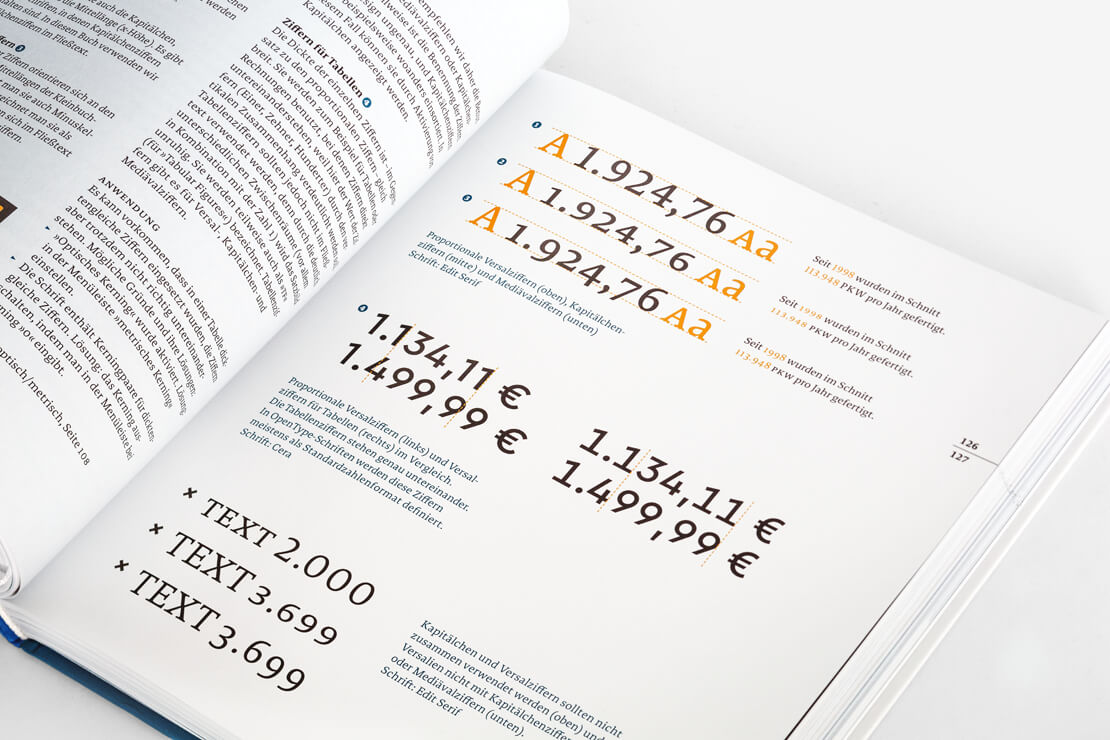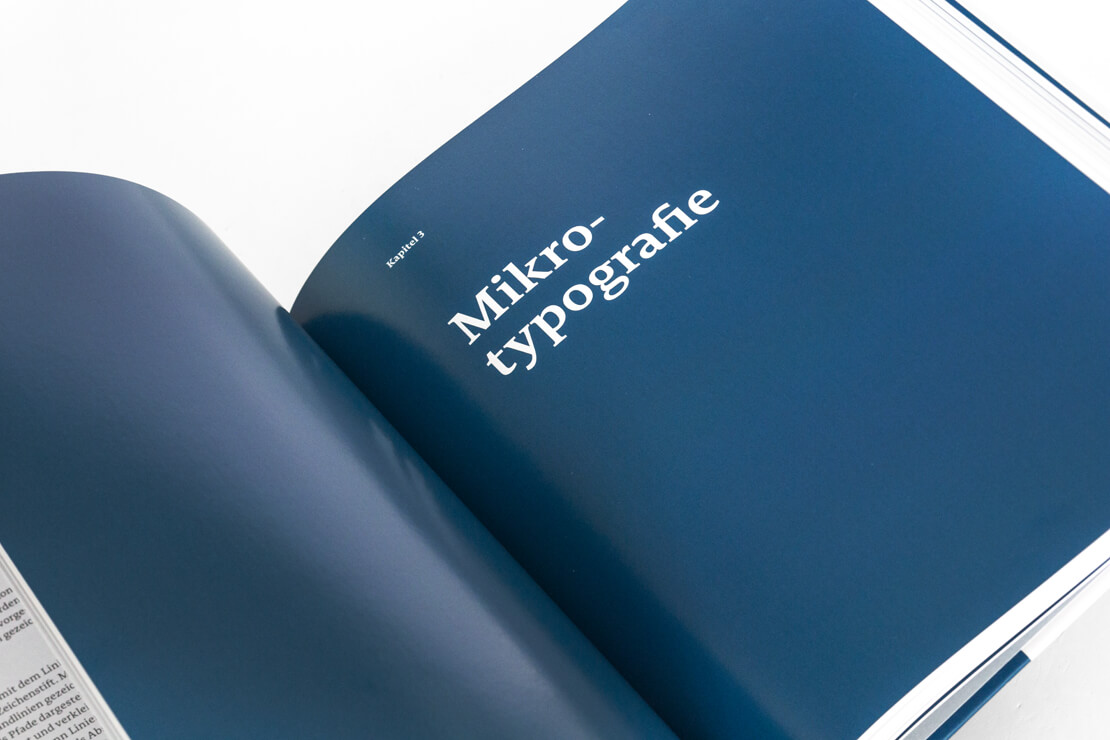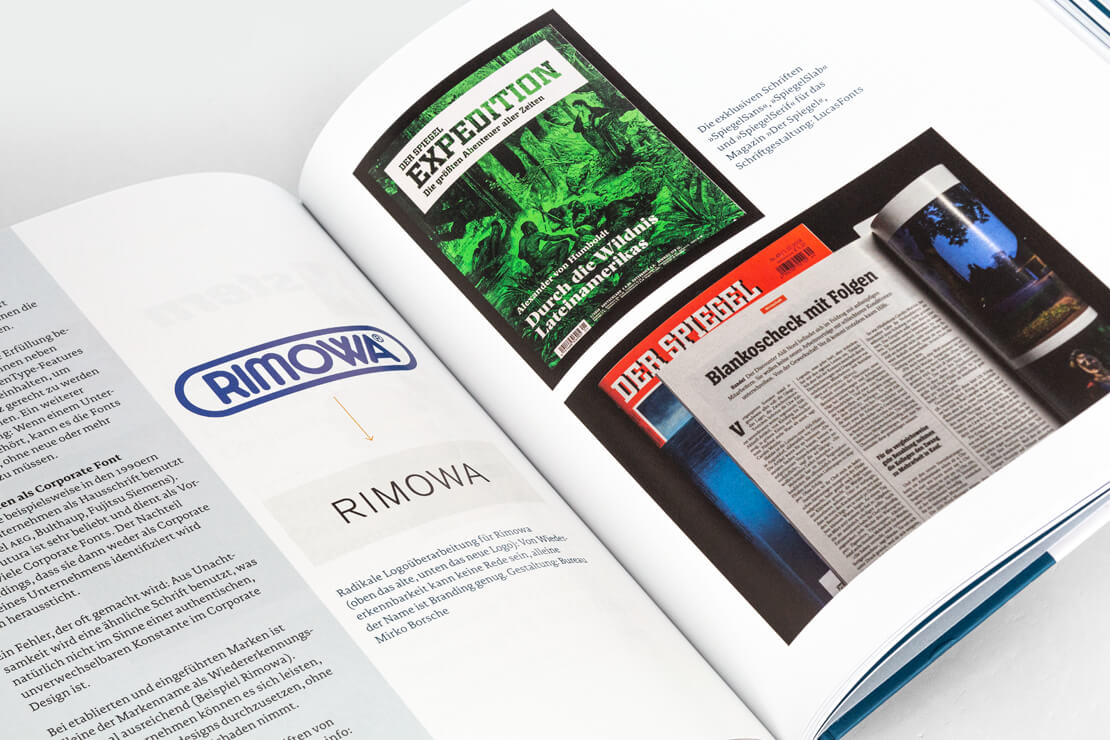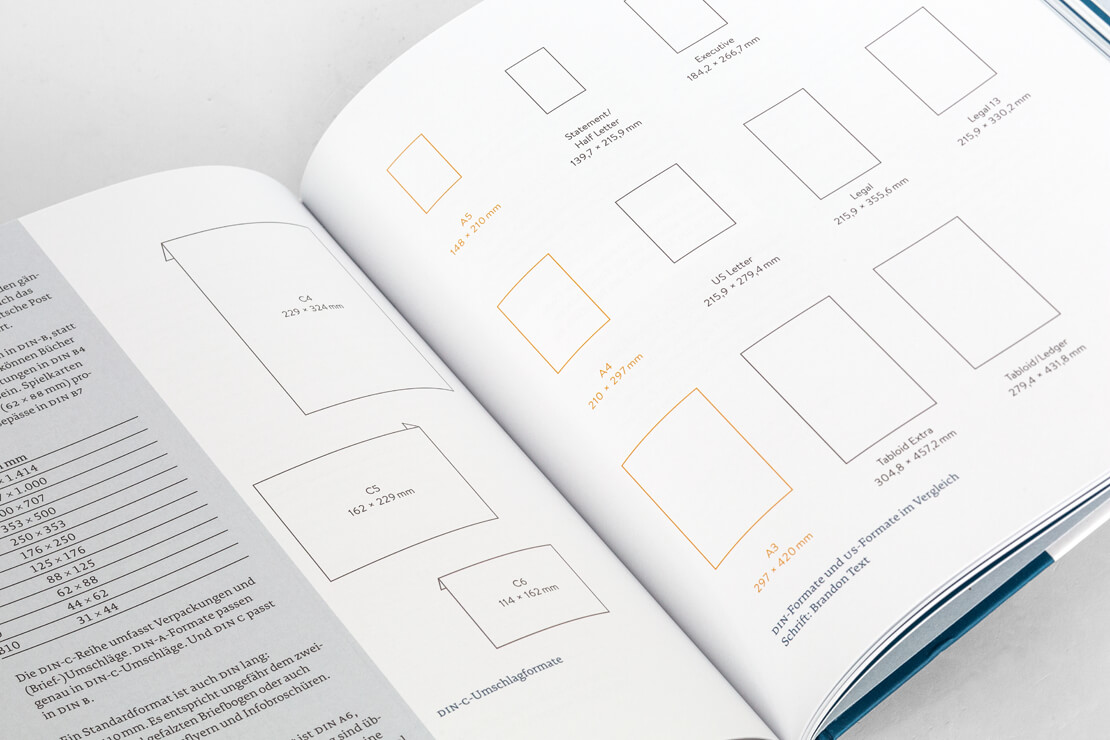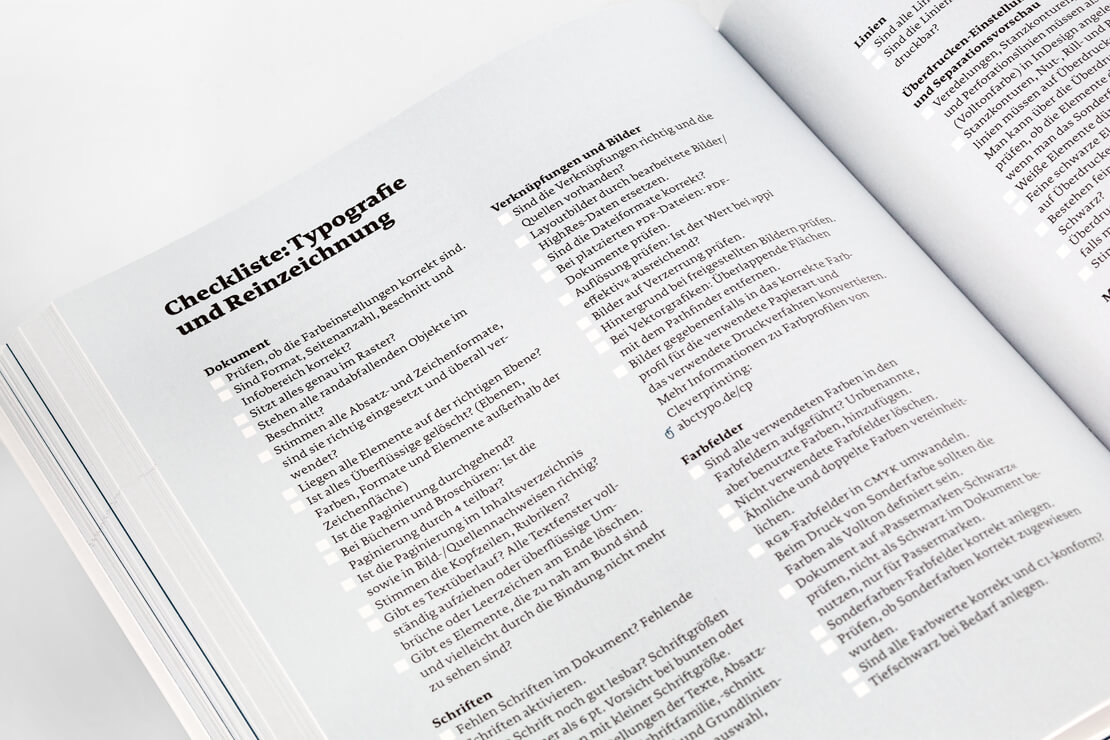
Das ABC der Typografie
Natalie Gaspar und Patrick Marc Sommer fassen die Grundlagen der Typografie in einem Buch zusammen. Der Ratgeber beinhaltet zudem Definitionen, Hintergründe und Anwendungen für die tägliche Praxis.
Typografie wirkt bereits, bevor man mit dem Lesen beginnt. Bereiche wie Schriftart, Schriftgröße, Zeilenabstand, Zeilenlänge und Co. werden intuitiv vom Betrachter wahrgenommen. Wie man die Regeln der Typografie nutzen kann, um gezielt Inhalte zu transportieren oder bestimmte Stimmungen einfangen zu können, erklärt dieses Buch.
Neben den »Grundlagen der Schrift« geht es in den jeweiligen Kapiteln um »Layout und Satz«, »Mikrotypografie«, »Schrift im Kontext«, »Digitale Typografie« und »Schriftgeschichte«. Gezeigt wird beispielsweise, wie man Schriften auswählt und kombiniert, Apostrophe richtig setzt, mit Satzspiegeln und Gestaltungsrastern arbeitet oder Weißraum nutzt.
Aber auch Bereiche wie Ligaturen, Laufweite, Versalsatz, Trennregeln, Einschübe, optischer Randausgleich, Paginierung, Papierformate oder Typografie im Webdesign kommen nicht zu kurz und wurden mit verständlichen Erklärungen versehen. Ergänzung zu den Ausführungen der beiden Autoren gibt es Gastbeiträge von Persönlichkeiten aus dem Typografie- und Designbereich.
»Das ABC der Typografie« eignet sich als Ratgeber für Kreative, die täglich mit Typografie umgehen oder auf der Suche nach einem Nachschlagewerk sind.